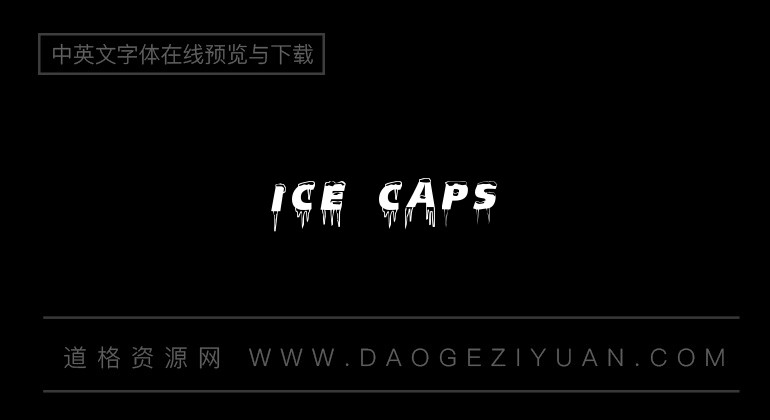
Ice Caps
Ice Caps 是一种符号字体,由设计师 Ray Larabie 创造,旨在模仿北极地区的冰山和冰川的感觉。它是一种装饰性的字体,适用于标题、海报、标志等设计。 Ice Caps 的特点是字母和数字都有尖锐的棱角,仿佛是从冰块中凿出来的一样。这种字体的颜色通常是白色或浅灰色,因为它们类似于冰或雪,与深色背景形成鲜明对比。Ice Caps 也有一些变体,例如 Ice Caps Bold 和 Ice Caps Italic,以满足不同的设计需求。
Ice Caps是一款非常不错的手写艺术字体,具有很好的视觉感,适合于文化类的宣传设计、商业类品牌的广告和产品包装设计以及个性化文字排版等较多场景。